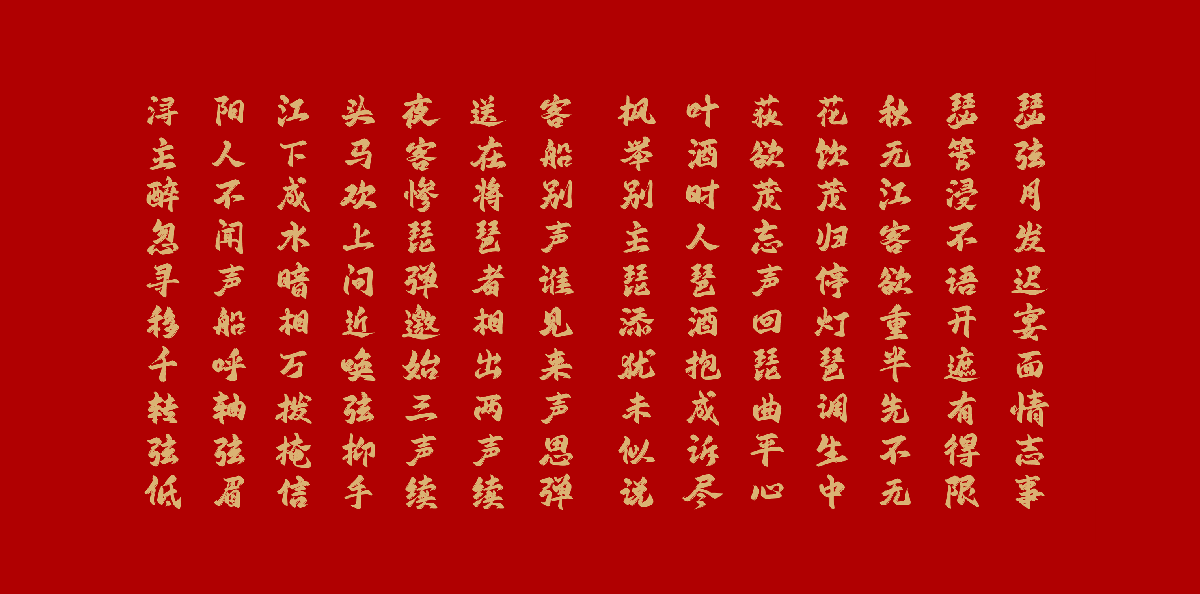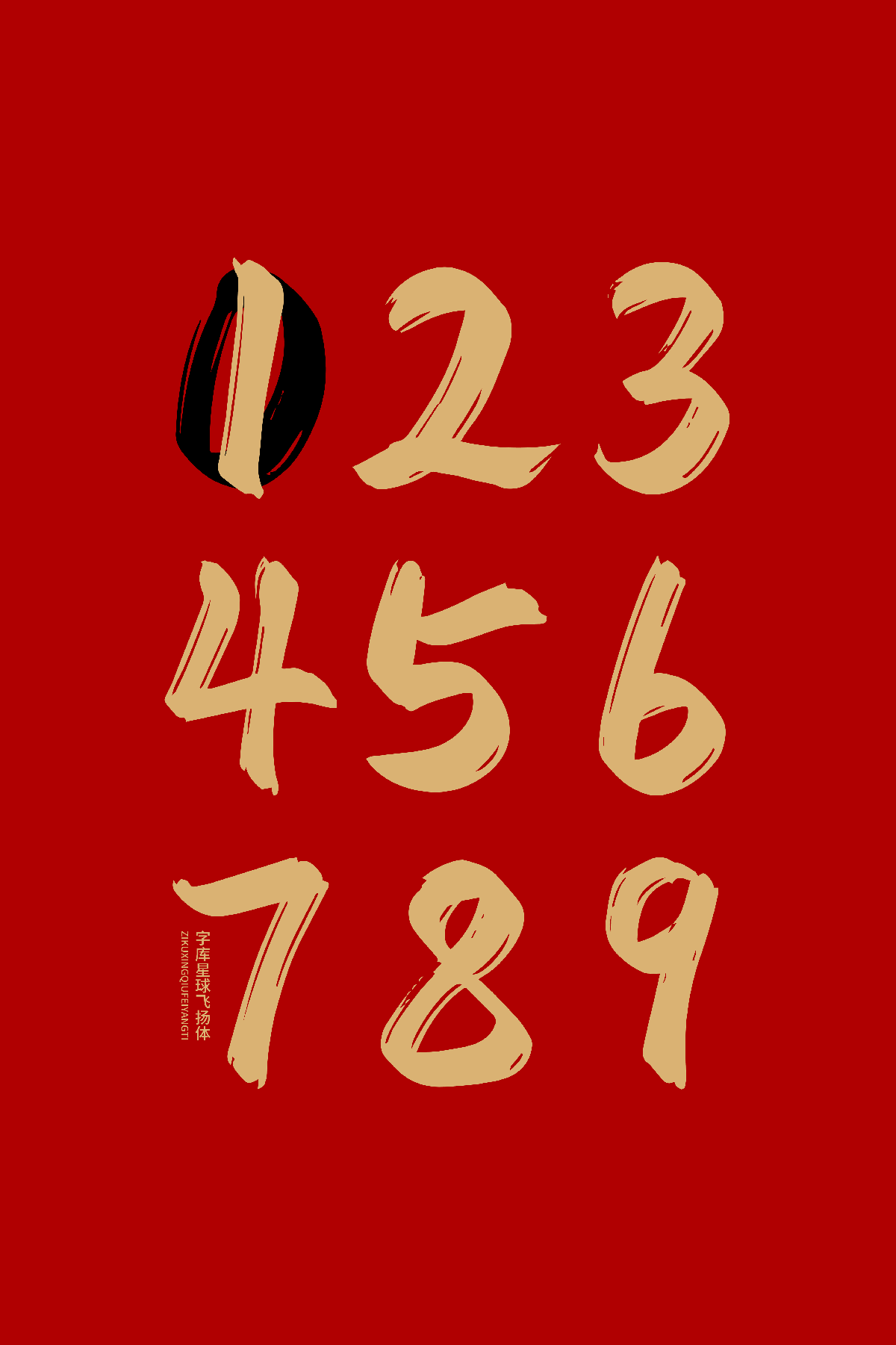
字库星球飞扬体是字库星球与甜奈网络深度合作、精心设计的一款免费可商用中文书法字体。
字库星球飞扬体融合传统书法美学与现代设计理念,呈现出潇洒写意、逸趣横生的独特风格。笔画灵动且富有变化,整体结构流畅自然,展现出别具一格的艺术气质,能够传递出飒爽流畅的视觉气场,有效烘托出热情洋溢的氛围。
字库星球飞扬体风格独特,字形笔画流畅,适用于各类书法或标题场景,助力打造极具吸引力的视觉呈现。